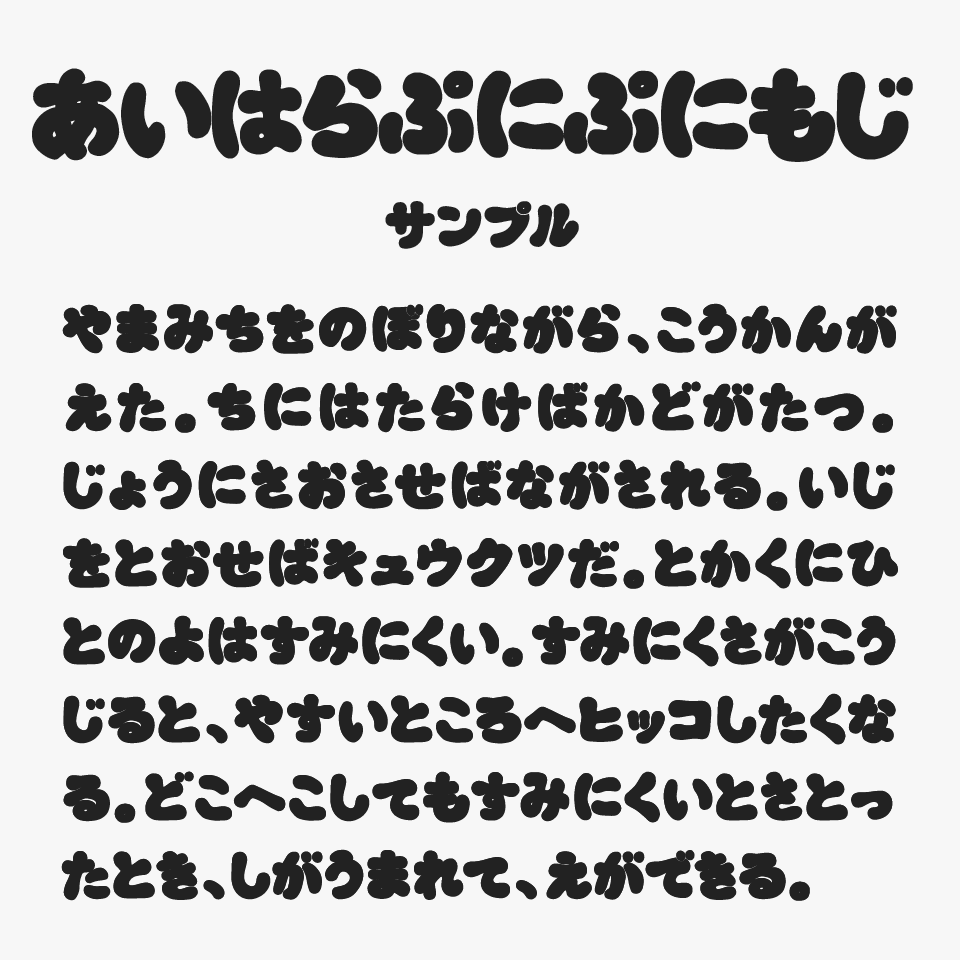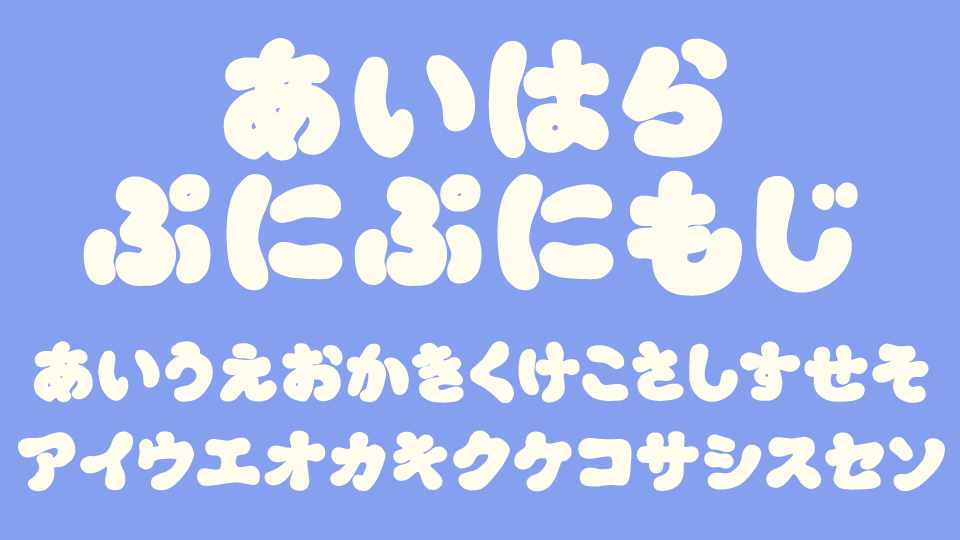
あいはらぷにぷにもじフォントは、ぷにっとした弾力を感じる丸みのあるシルエットが可愛らしいデザインフォントです。
手書きっぽさのあるゆるさと、太めの線幅と大きく丸められた角によって、やさしく親しみやすい印象を与えながら、一文字一文字にしっかりとしたインパクトあるフォントです。かわいらしさがありつつも読みやすく、ポップで元気な雰囲気を自然に演出できるため、幅広いデザインで活躍するフォントです。
子ども向けコンテンツやポップなデザインとの相性が良く、お菓子のパッケージ、YouTubeサムネイル、SNS投稿、LINEスタンプ、イベントチラシなどにぴったりです。
あいはらぷにぷにもじフォントを、ほかのぷるっとした可愛らしいフォントと比較してみると、名前の通り“ぷにぷに”とした弾力を感じるフォルムが特に魅力のフォントです。
ぷっくり系フォントは、丸みやボリューム感を強調したものが多いですが、あいはらぷにぷにもじは、一文字一文字にやわらかな膨らみがあり、まるでゼリーやマシュマロのようなもちもちとした質感を感じさせます。
収録文字は、ひらがな・カタカナ・記号が収録されています。